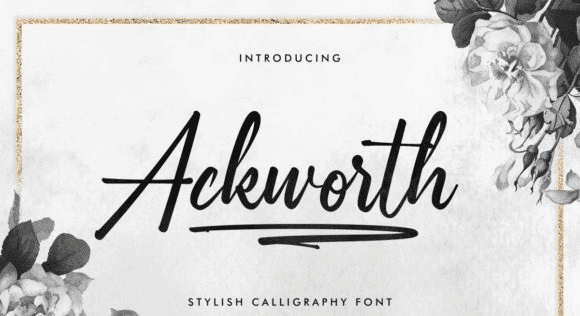
Название: Ackworth Font (2021)
Ackworth - это смелый каллиграфический шрифт со сложными символами, стильными штрихами и великолепными чередованиями.
Этот свободный шрифт идеально подходит для каллиграфии приглашений, роскошного брендинга, модных рекламных акций, титров песен и многого другого. Этот шрифт закодирован в PUA, что означает, что вы можете легко получить доступ ко всем глифам и штрихам!
Название: Ackworth Font (2021)
Ackworth - это смелый каллиграфический шрифт со сложными символами, стильными штрихами и великолепными чередованиями.
Этот свободный шрифт идеально подходит для каллиграфии приглашений, роскошного брендинга, модных рекламных акций, титров песен и многого другого. Этот шрифт закодирован в PUA, что означает, что вы можете легко получить доступ ко всем глифам и штрихам!